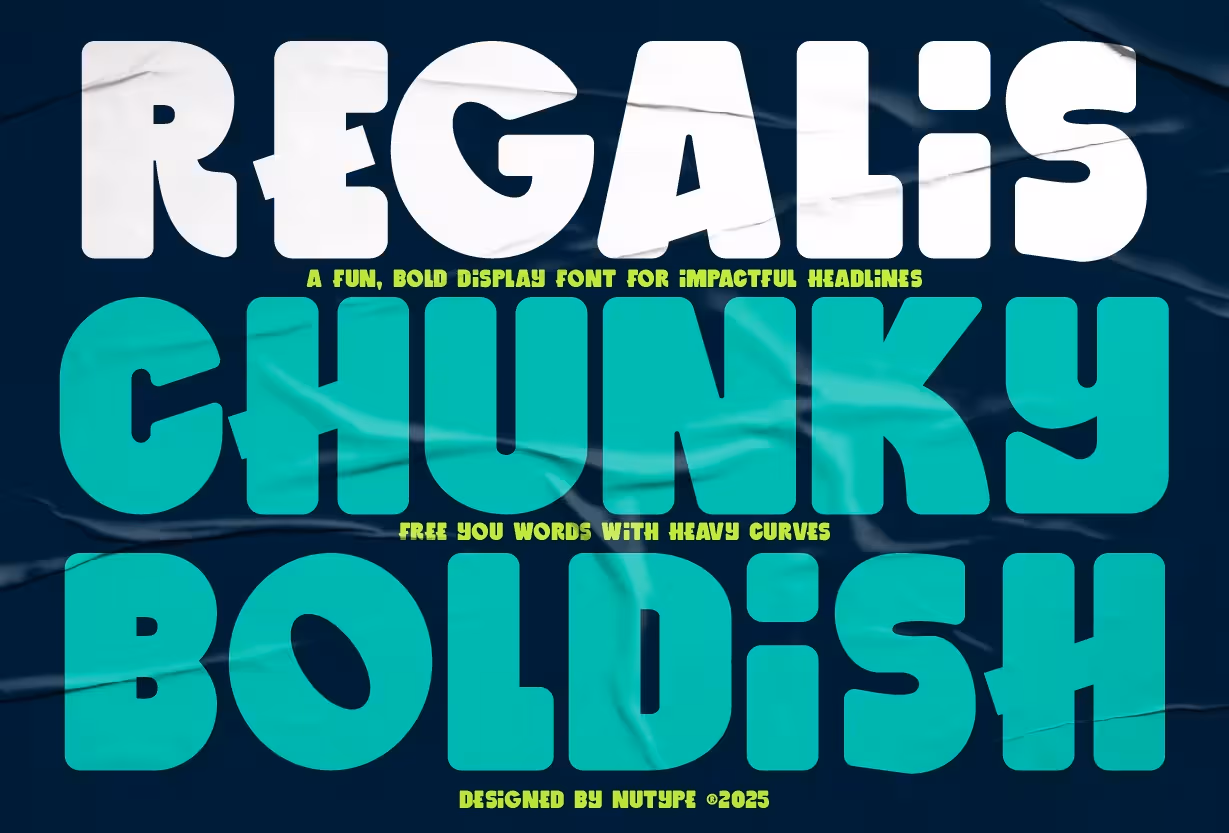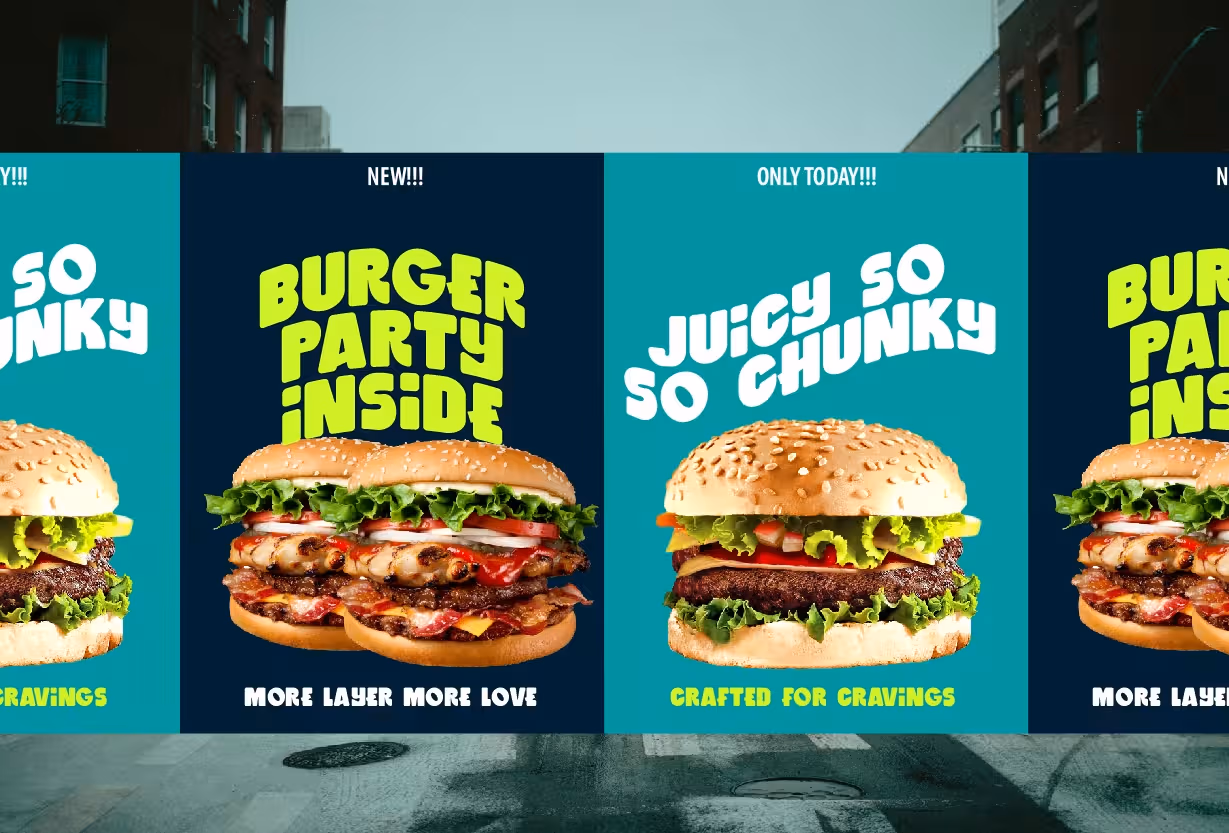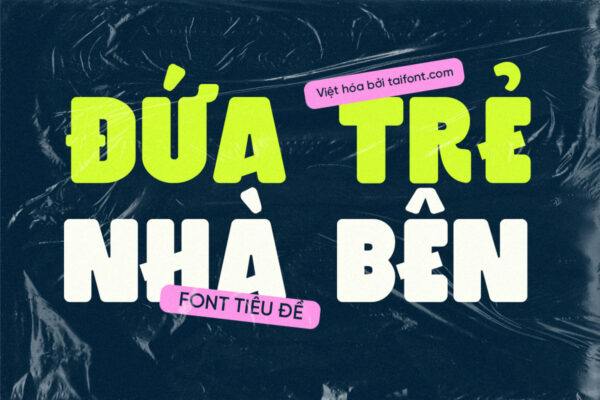
Giới thiệu về Font TF Regalis Việt hóa
TF Regalis Việt hóa là một font chữ không chân (sans-serif) nổi bật với thiết kế to, đậm, tròn trịa và đầy đặn. Font này mang đến vẻ ngoài vui tươi, dễ thương và thân thiện, gợi cảm giác về sự hồn nhiên, sự ấm áp và một chút tinh nghịch, lý tưởng để tạo điểm nhấn độc đáo và thu hút mọi ánh nhìn, đặc biệt trong các thiết kế dành cho trẻ em hoặc các lĩnh vực liên quan đến ẩm thực.
Với đặc điểm là hình dáng tròn mềm mại, nét chữ to đậm và tính thẩm mỹ cao, Regalis là lựa chọn hoàn hảo cho các thiết kế muốn truyền tải sự vui tươi, gần gũi và sự đáng yêu:
- Thiết kế trẻ em: Hoàn hảo để sử dụng trên bìa sách, tiêu đề chương, hoặc các lời dẫn trong các cuốn sách, truyện tranh, truyện cổ tích dành cho trẻ em. Font này giúp tạo không khí thân thiện, vui tươi và thu hút sự chú ý của các bạn nhỏ.
- Thiết kế ẩm thực: Phù hợp để sử dụng trên menu, bao bì sản phẩm, poster quảng bá món ăn, hoặc các ấn phẩm truyền thông của nhà hàng, quán ăn, quán cà phê. Font này giúp món ăn trở nên hấp dẫn hơn, tạo cảm giác ngon miệng và thu hút sự chú ý của thực khách.
- Thiết kế áo thun: Lý tưởng để in các câu trích dẫn, thông điệp cá nhân hoặc họa tiết chữ lên áo phông, áo hoodie. Nét chữ to và bo tròn của font sẽ giúp áo thun trở nên nổi bật, phong cách và truyền tải thông điệp một cách cá tính, thu hút, đặc biệt là với đối tượng trẻ em hoặc giới trẻ.
- Thiết kế bao bì sản phẩm: Tuyệt vời để sử dụng trên nhãn mác, bao bì của các sản phẩm dành cho trẻ em, đồ chơi, đồ ăn vặt, hoặc các sản phẩm có phong cách vui tươi. Font này giúp sản phẩm trở nên nổi bật và thu hút.
Với TF Regalis Việt hóa, bạn có thể dễ dàng thổi hồn vui tươi, sự hồn nhiên và vẻ đẹp độc đáo vào các thiết kế, tạo ra những sản phẩm không chỉ đẹp mắt mà còn đầy cảm xúc và sức hút đặc biệt.
Font Việt hóa TF Regalis